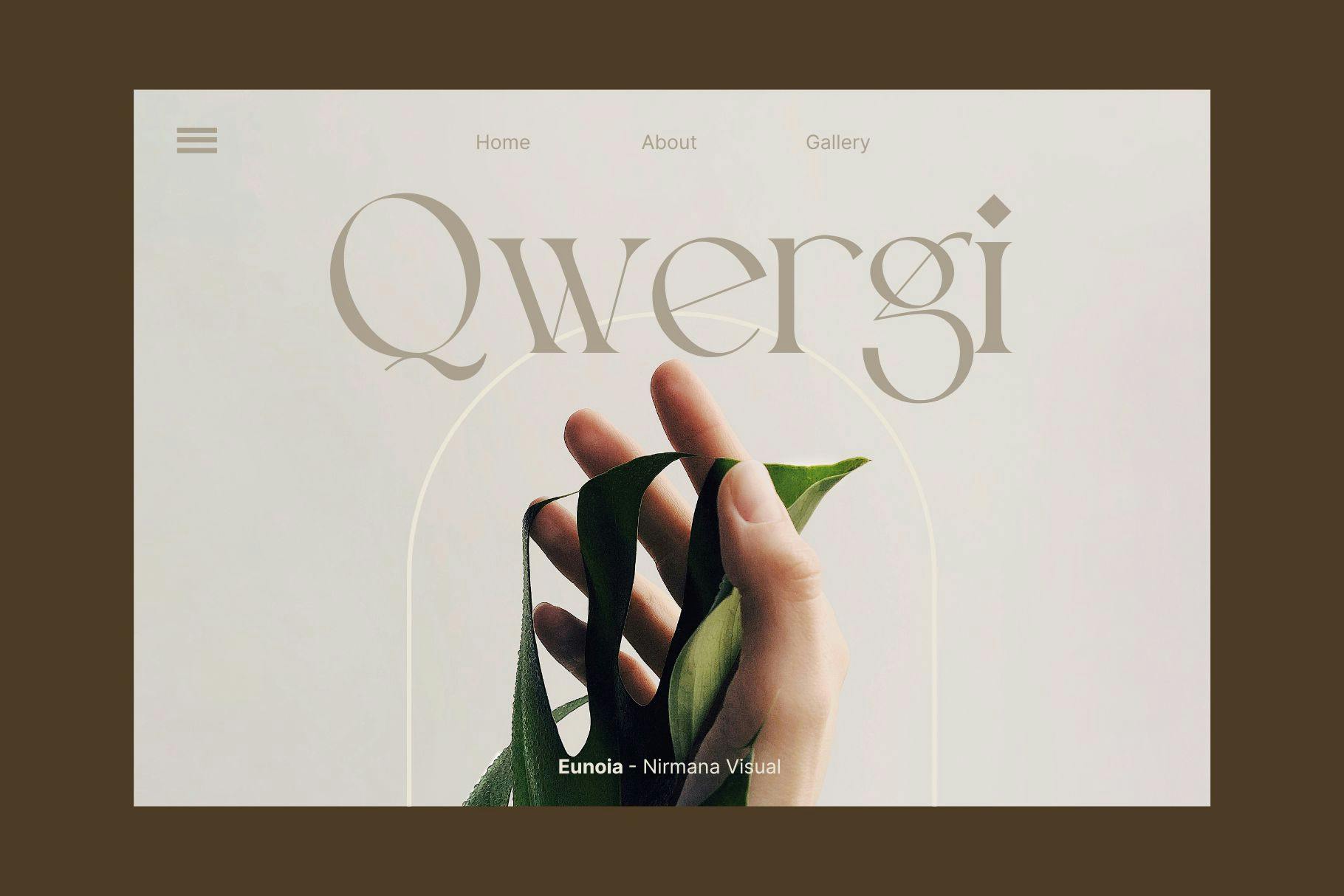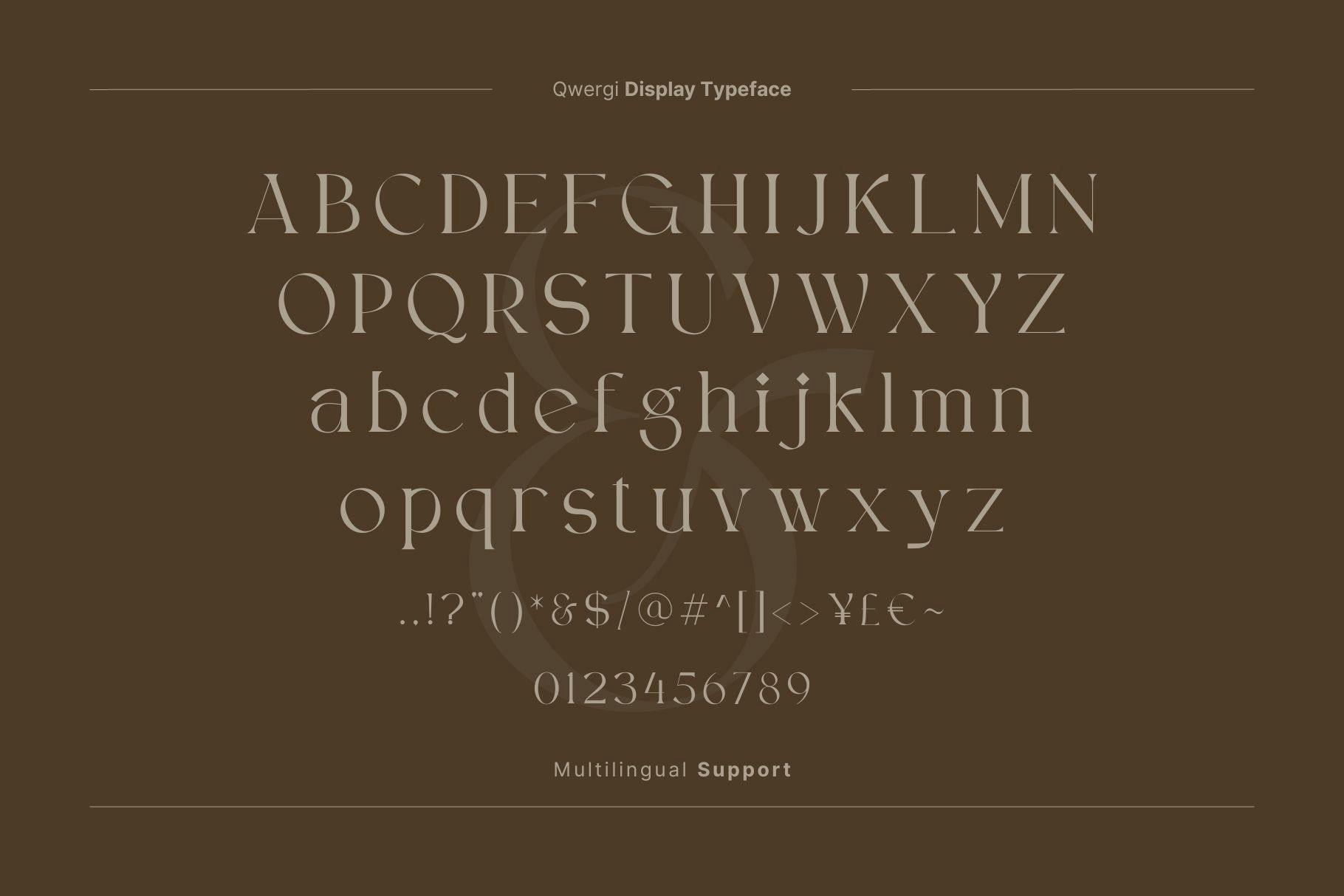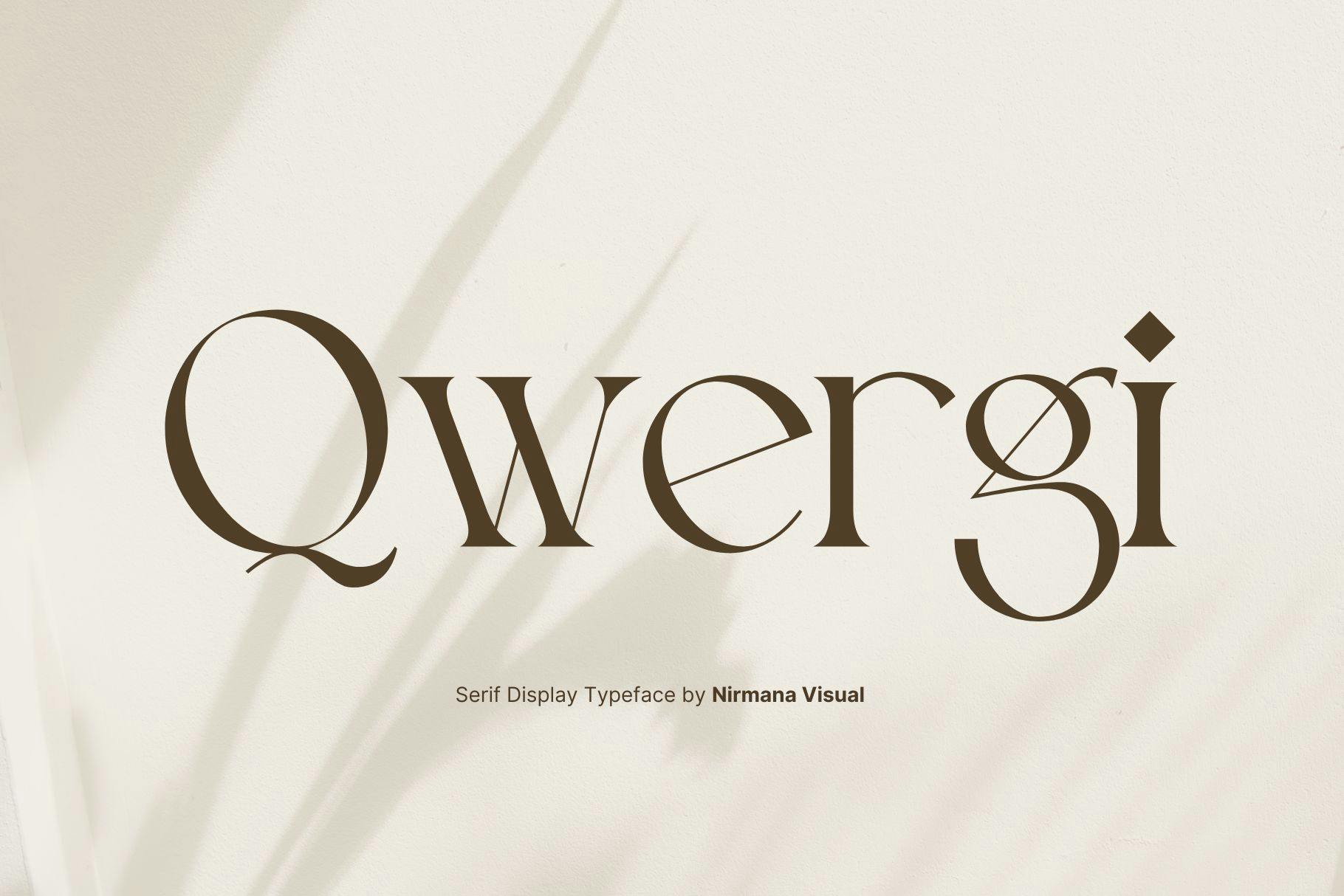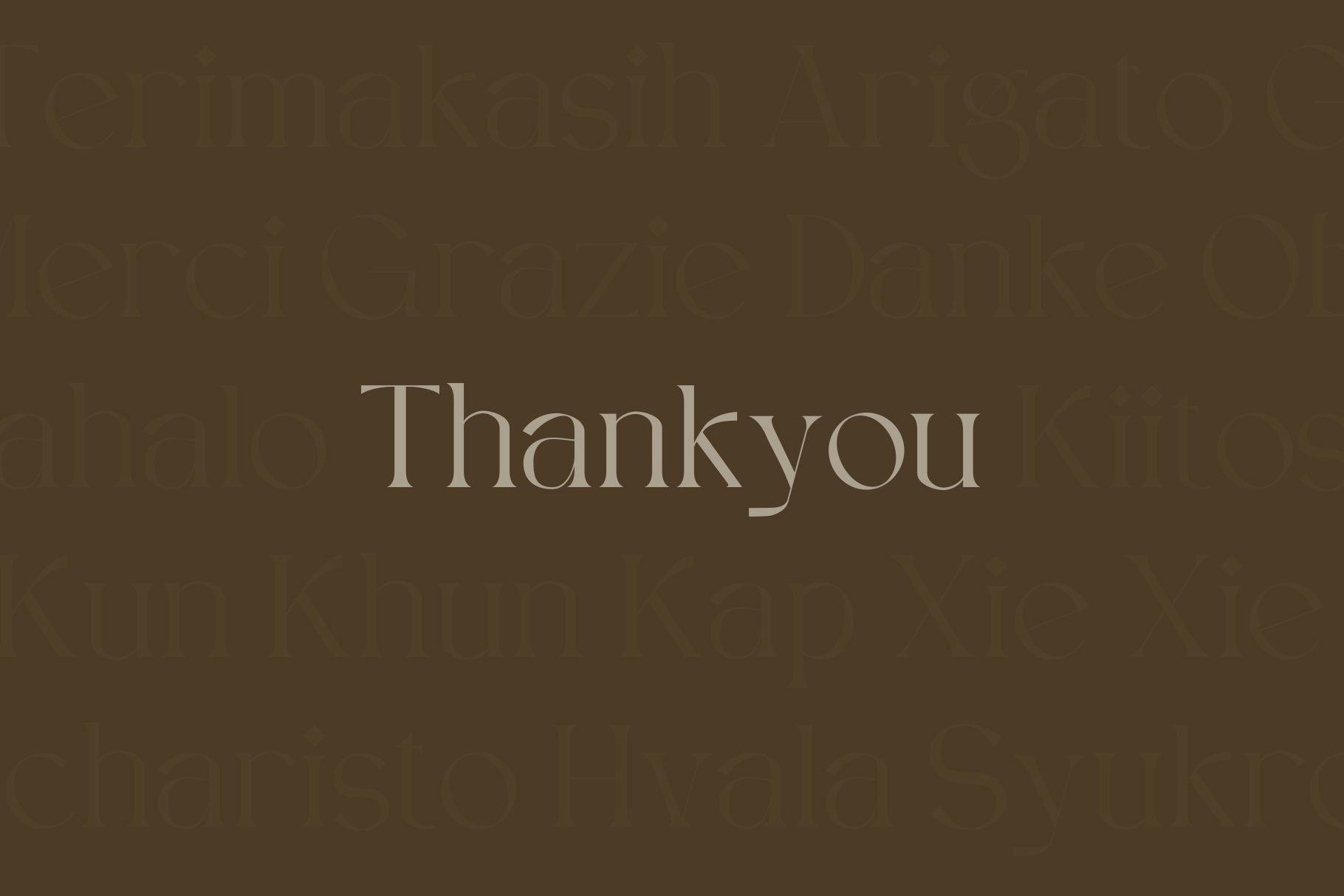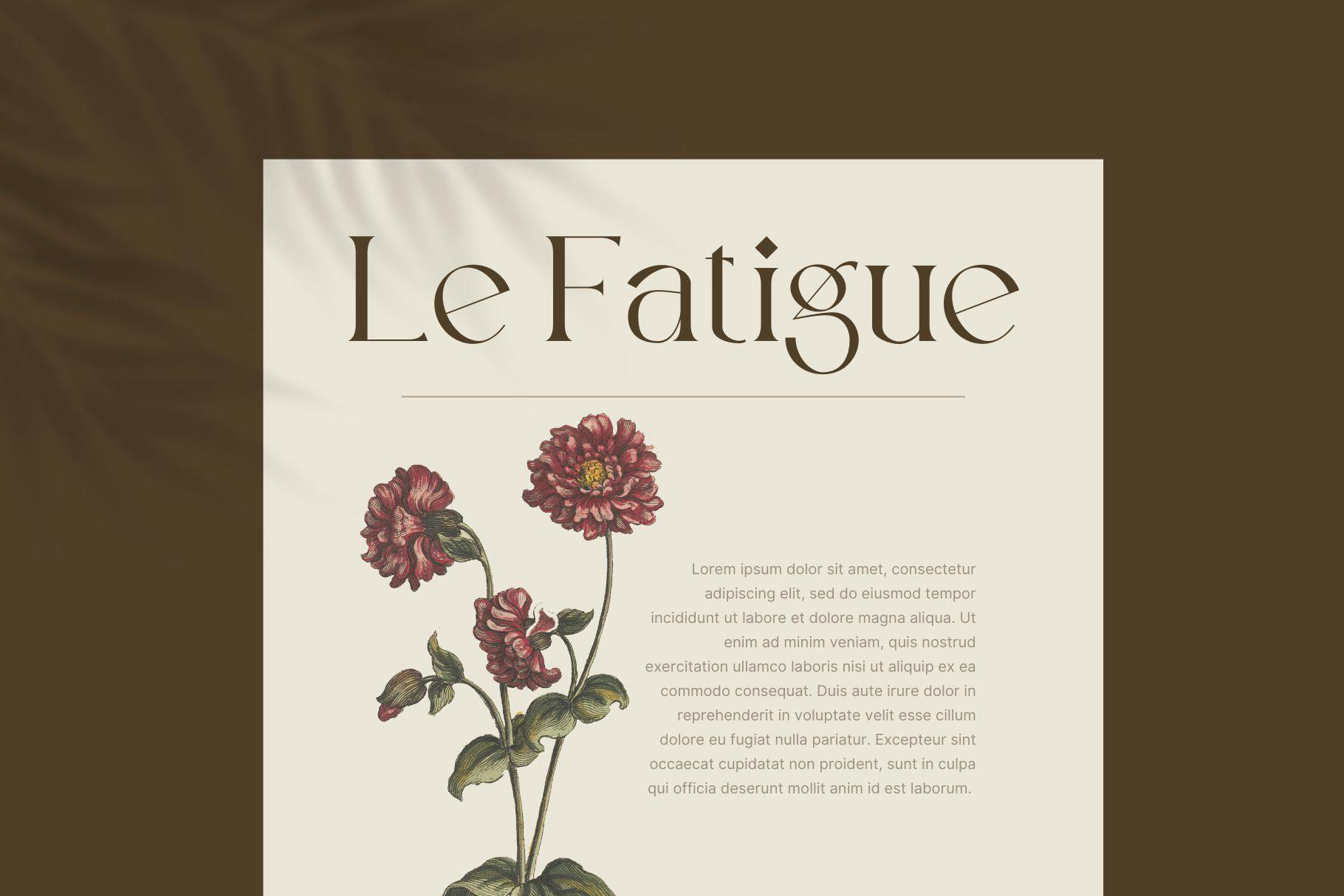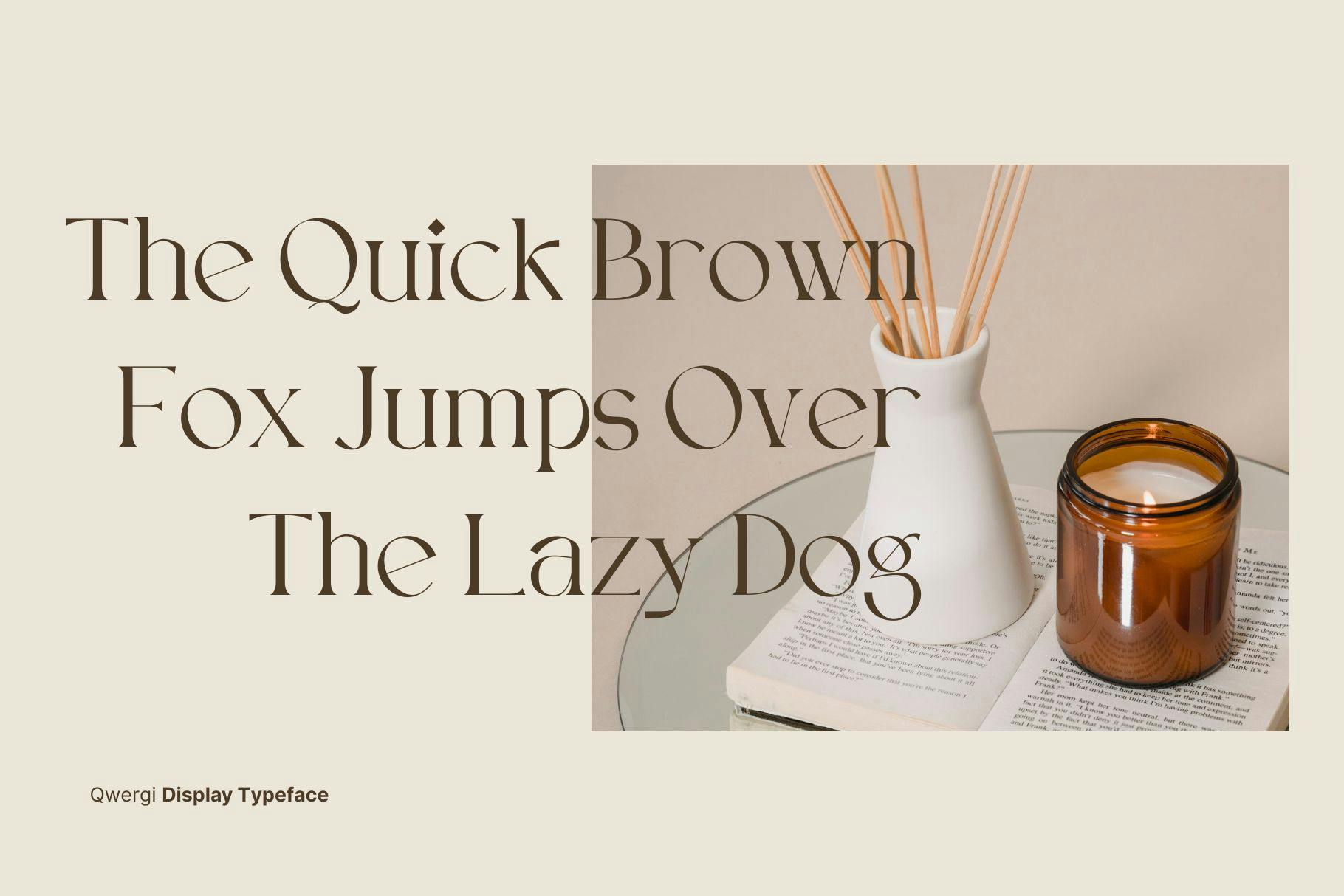
Qwergi، یک فونت سریف معاصر است که زیبایی خاصی به پروژههای طراحی شما میبخشد.
فونت Qwergi هارمونی تایپوگرافی زیبایی را برای تنوعی از پروژههای طراحی، از جمله لوگو و برندینگ، پستهای شبکههای اجتماعی، تبلیغات و طراحی محصولات ارائه میدهد.